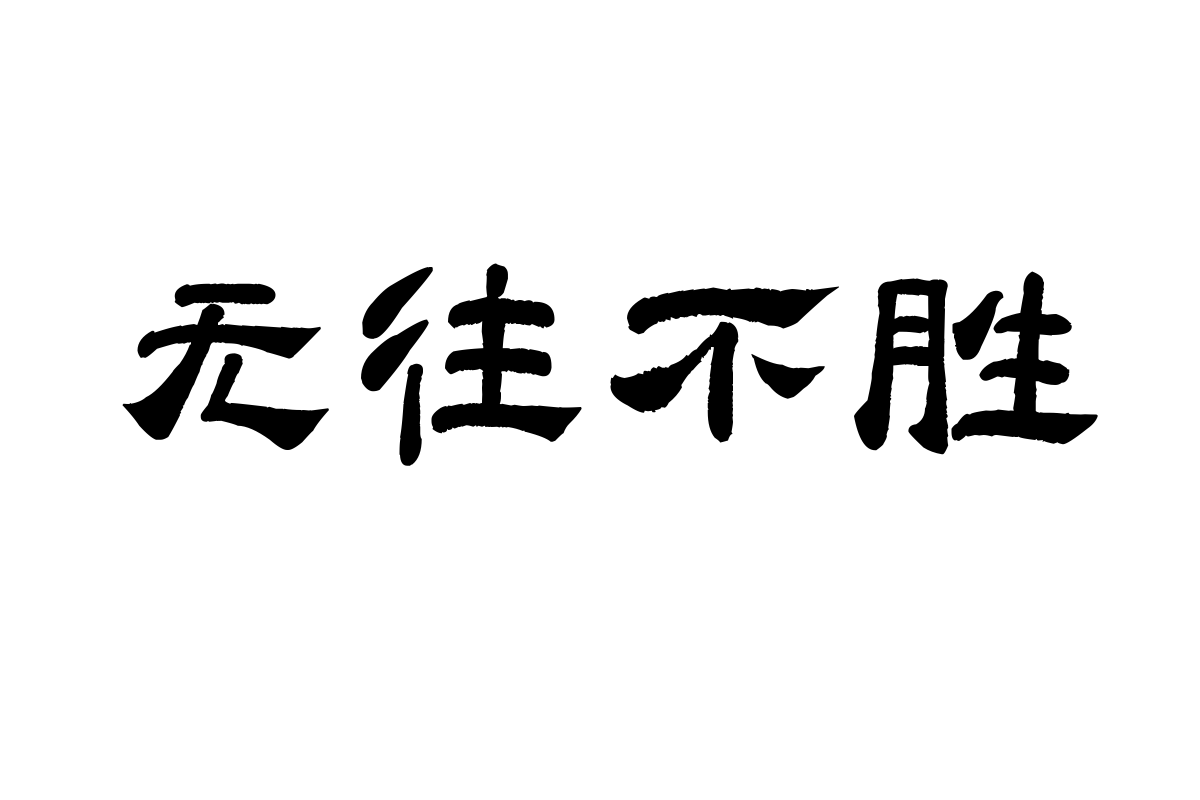
也字工厂逐日汉隶体是一款专为汉字设计的艺术字体,具有独特的风格和表现力。这款字体以简洁、流畅的线条为基础,通过巧妙的笔画组合和结构布局,呈现出一种古朴而优雅的视觉效果。
在设计上,也字工厂逐日汉隶体注重对汉字形态的提炼和简化,使得每个字都显得更加清晰、易读。同时,该字体还融入了一些现代元素,使其既保留了传统书法的韵味,又不失时尚感。